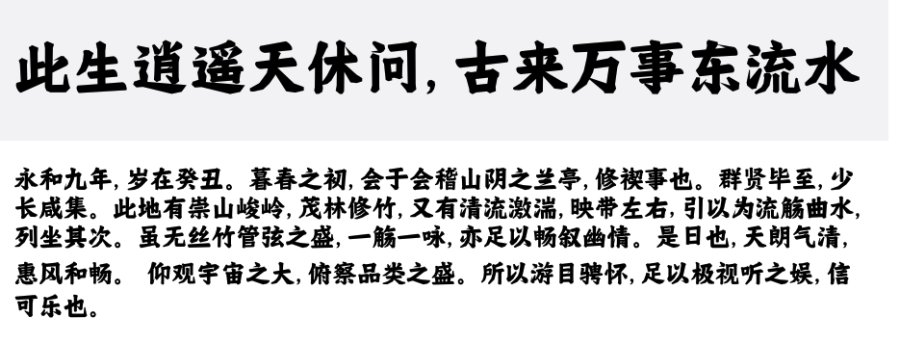
简约大气的百搭字体,是设计们的最爱。用最简单的笔画和线条来表现高级感,让字体也有留白!这类字体笔画干净利落,没有过于复杂的图形装饰,字体骨架轮廓清晰,简约却不失时尚感。
上首逍遥体,简体中文约6763字,字体笔画简约,随性而有个性,灵巧伶俐,橫笔两边导圆,竖笔收笔时带笔锋,撇捺收笔也带笔锋。适用于搭配标志、广告标语、商业广告等。